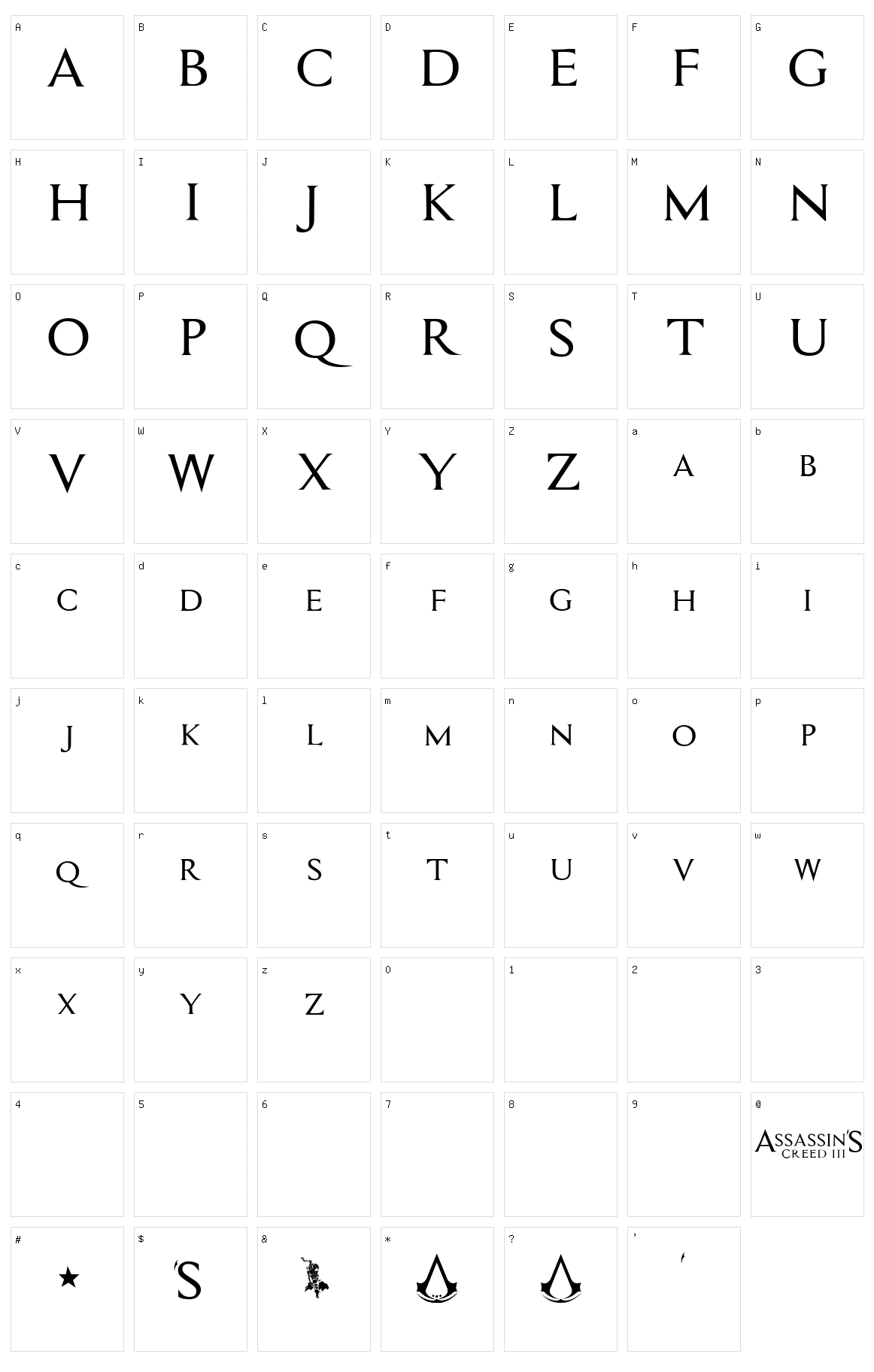
x ASSASSIN'S CREED FONT x
Font name: ASSASSIN'S CREED (PSP Collection) - Latin Decorative font (versione 1.0)
Type designer: P. A. Vannucci
ASSASSIN'S CREED font: direttamente dal videogame distribuito dalla UBISOFT, il font inedito per tutti
gli estimatori del gioco. Da notare il ritocco necessario in Photoshop per conferire, alla titolazione, l'originale bordatura.
ASSASSIN'S CREED font: directly from the Best videogame by UBISOFT,the original font for all lovers. Use ADOBE Photoshop for the original border from title.